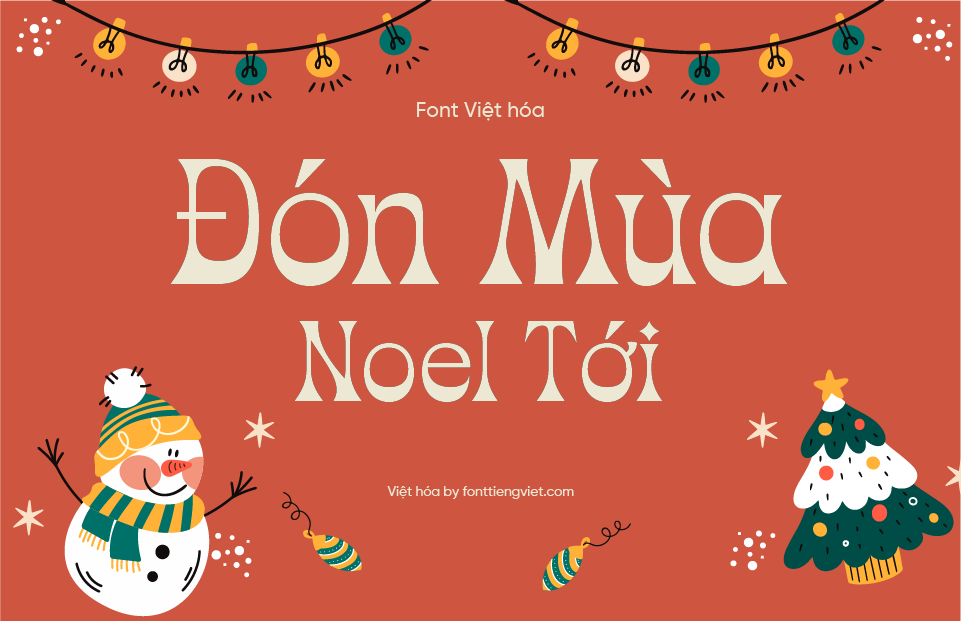
Font Việt hóa 1FTV VIP Christmas Blink
Giới thiệu về bộ Font Việt hóa 1FTV VIP Christmas Blink
Chào mừng bạn đến với thế giới sáng tạo đầy màu sắc dành cho học sinh và thầy cô giáo. Trong không khí rộn ràng của mùa Giáng sinh, việc sở hữu một bộ Font Việt hóa 1FTV VIP Christmas Blink chất lượng là điều vô cùng cần thiết. Đây không chỉ là một phông chữ thông thường mà còn là công cụ giúp các em học sinh tự tay thiết kế những tấm thiệp chúc mừng ý nghĩa gửi tặng cha mẹ và bạn bè. Font Miễn Phí luôn nỗ lực mang đến những tài nguyên tốt nhất để khơi dậy niềm đam mê nghệ thuật trong môi trường giáo dục Việt Nam.
Đặc điểm thiết kế độc đáo của bộ font
Bộ phông chữ này gây ấn tượng mạnh mẽ nhờ những đường nét uốn lượn mềm mại, mô phỏng hình ảnh ánh đèn lung linh và những dải ruy băng trang trí Noel. Các ký tự được chăm chút tỉ mỉ, đảm bảo tính thẩm mỹ cao mà vẫn giữ được độ rõ nét khi in ấn hoặc trình chiếu trên bảng điện tử. Đặc biệt, phiên bản này đã được tối ưu hóa hoàn toàn cho tiếng Việt, giúp người dùng không gặp lỗi hiển thị dấu câu khi soạn thảo văn bản.
Ứng dụng Font Việt hóa 1FTV VIP Christmas Blink trong học tập
Các thầy cô giáo có thể sử dụng bộ chữ này để trang trí bài giảng điện tử thêm sinh động, giúp tiết học về văn hóa lễ hội trở nên lôi cuốn hơn đối với học sinh. Bên cạnh đó, các bạn trẻ có thể ứng dụng vào việc thiết kế báo tường, nhãn vở hoặc các sản phẩm đồ họa đơn giản trên lớp. Sự kết hợp giữa nét chữ nghệ thuật và thông điệp yêu thương sẽ tạo nên những kỷ niệm đẹp trong quãng đời học sinh hồn nhiên.